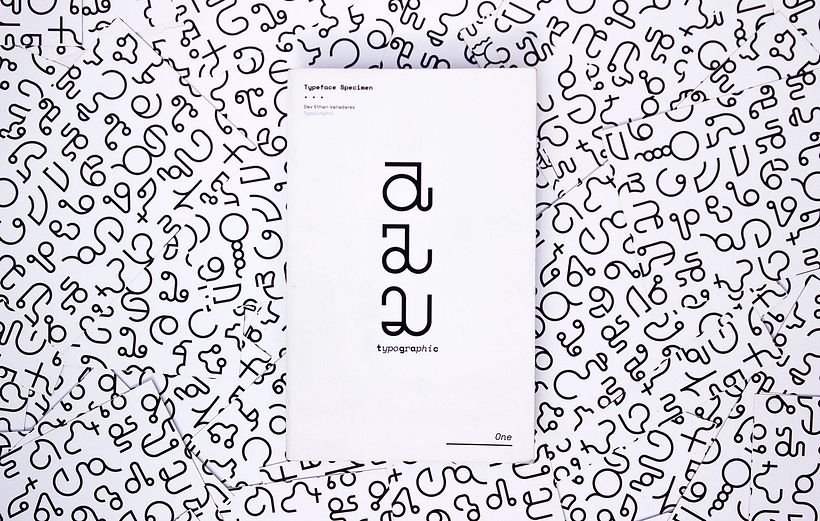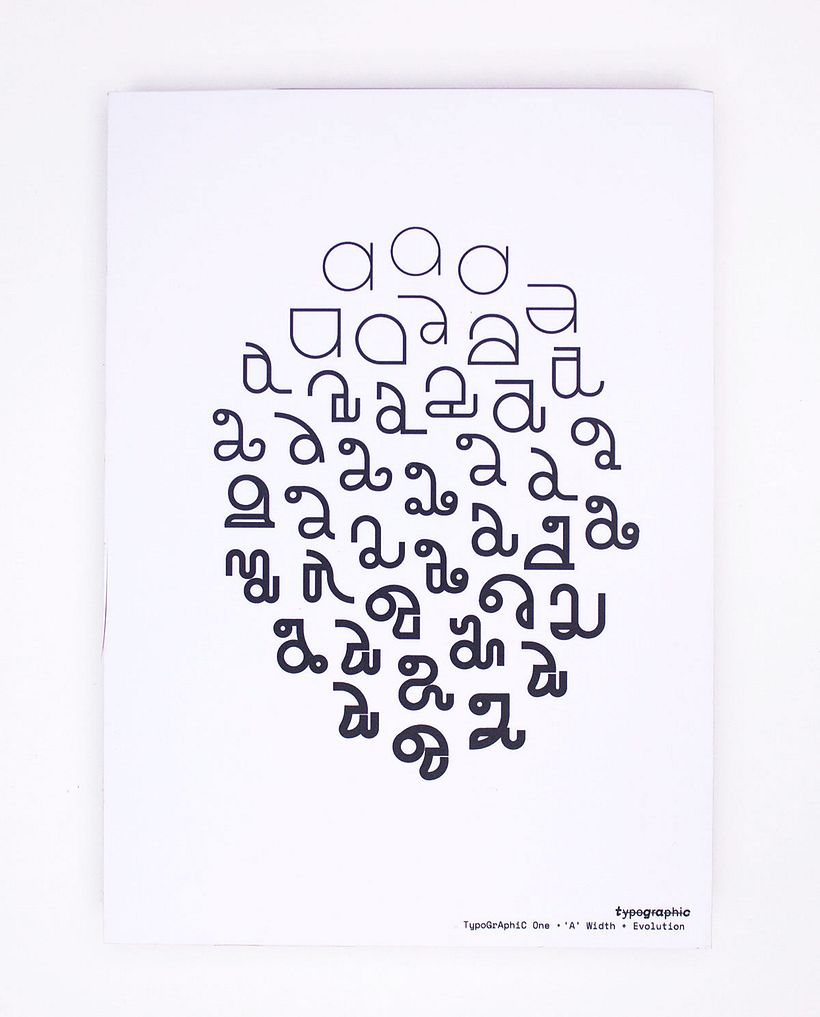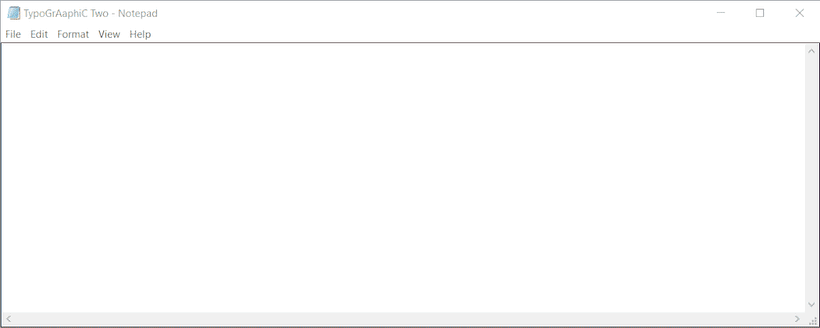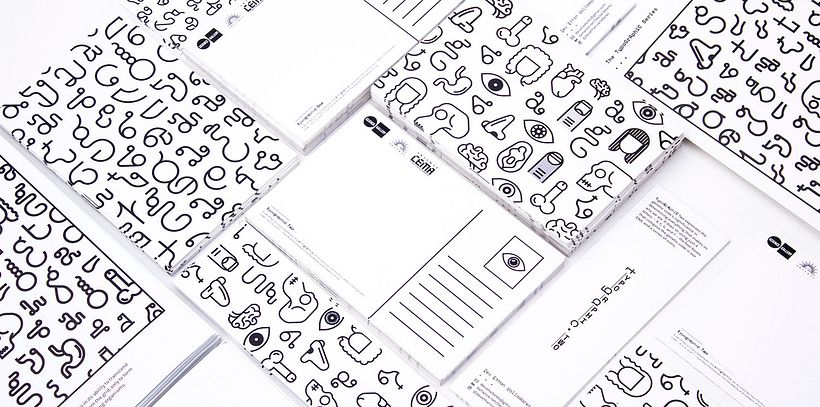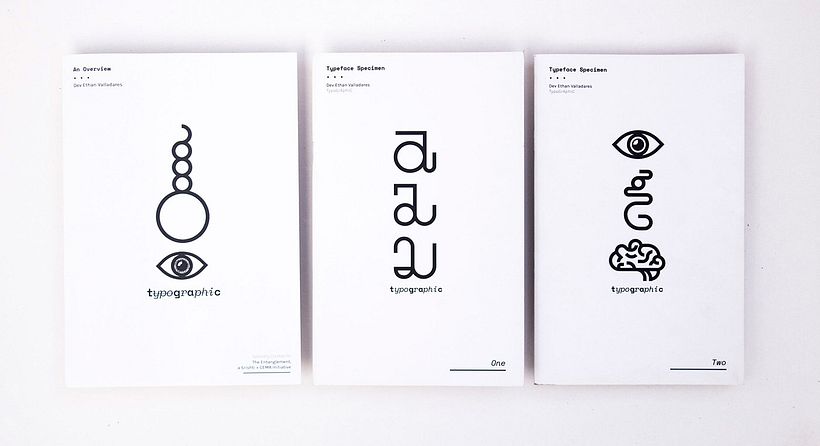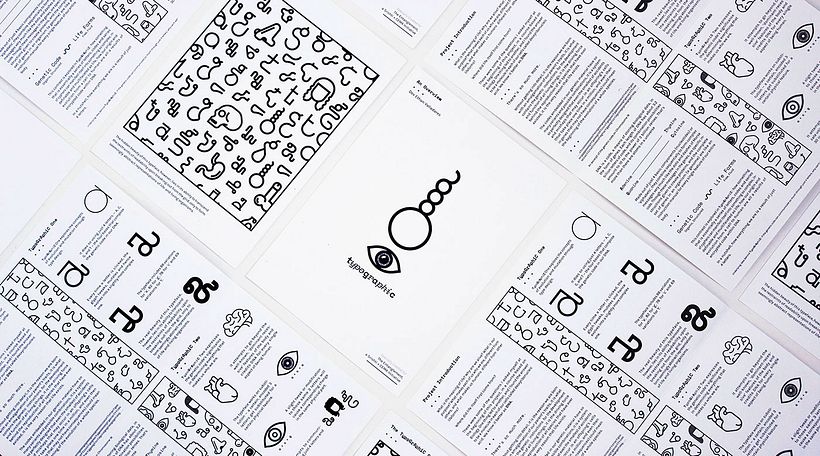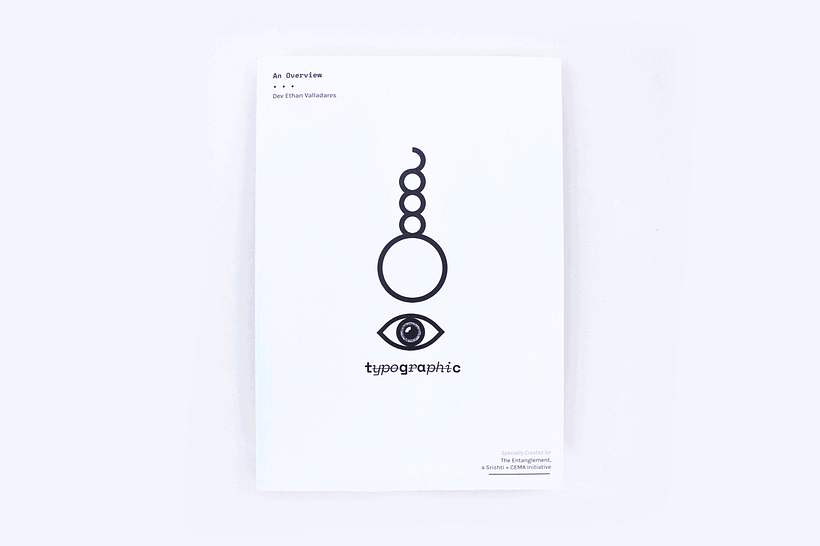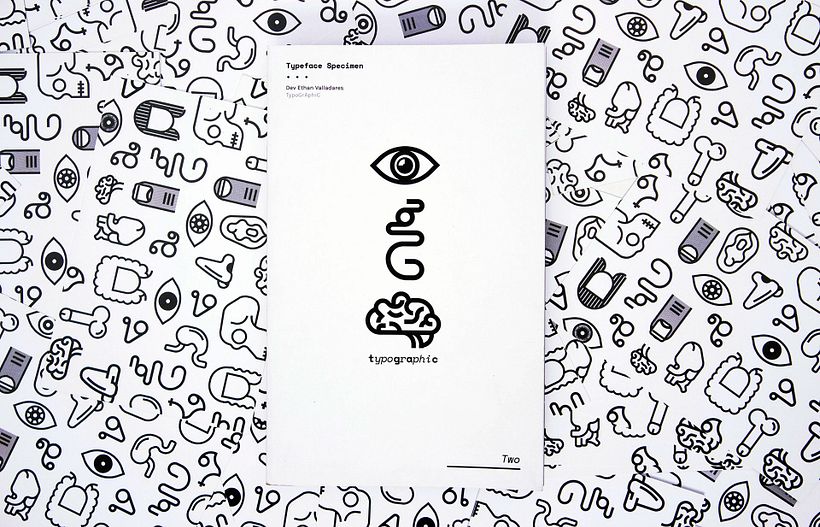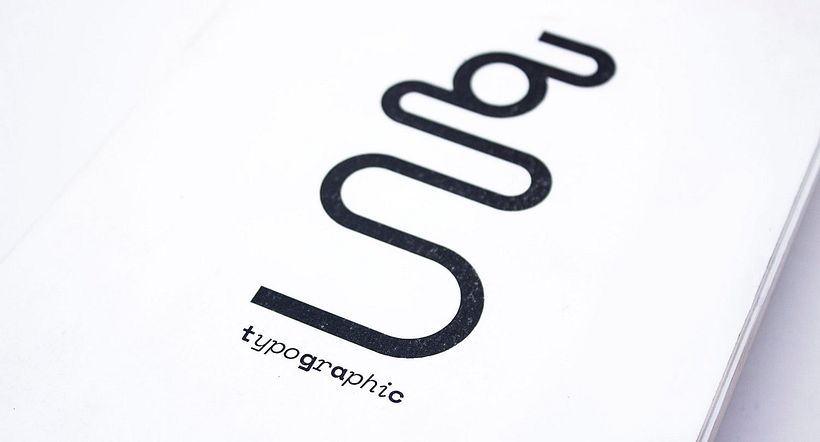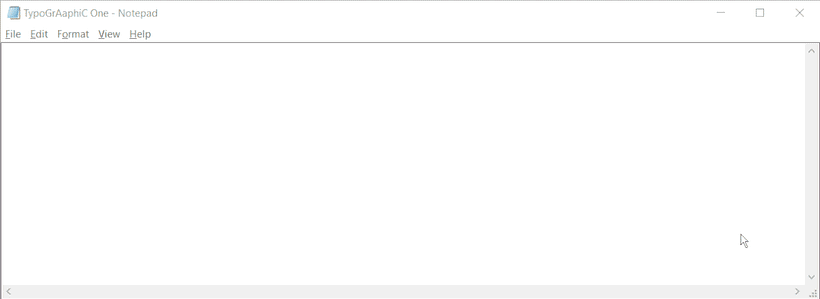
TypoGrAphiC, una tipografía basada en el ADN
Con apenas cuatro letras esta tipografía, diseñada a partir del ADN, es capaz de crear cientos de combinaciones.
Es el ácido desoxirribonucleico (a.k.a. ADN) el encargado de transportar las instrucciones genéticas del desarrollo y funcionamiento de todos los organismos vivos y de su transmisión hereditaria. Sin profundizar en términos técnicos podemos comprender que son estas moléculas, compuestas por apenas cuatro bases –adenina (A), citosina (C), guanina (G) y timina (T)– que, combinadas, las encargadas de configurar la herencia genética de cada individuo. El diseñador Dev Ethan Valladares ha tomado el comportamiento del ADN como modelo para desarrollar TypoGrAphiC, un set de tipografías que mutan y evolucionan a partir de cuatro glifos.
TypoGrAphiC One explora la idea de la evolución y representa ese proceso a través de la posibilidad de sustitución de glifos que ofrecen las tipografías OpenType. Sencillas figuras geométricas se vuelven cada vez más complejas. Cada una de las letras iniciales ofrece diferentes variables que permite ver la mutación de la tipografía frente a nuestros ojos. La letra A tiene 88 variaciones; la G, 82; la C, 78 y la T, 69.
TypoGrAphiC Two juega con la configuración que estas cuatro letras utilizan para definir características físicas reales en el ser humano. Así, en esta tipografía, una combinación de tres letras se sustituyen automáticamente por una parte del cuerpo, cuyas particularidades varían en función de la secuencia elegida, de la misma manera que lo hace la naturaleza al realizar diferentes composiciones en la vida real.
TypoGrAphiC es el proyecto pre-tesis de Dev Ethan Valladares, con el que ha querido hacer una reflexión profunda sobre el origen de la vida y el juego del azar en la configuración de las características físicas del ser humano.